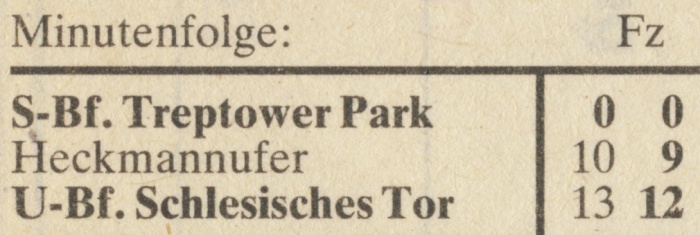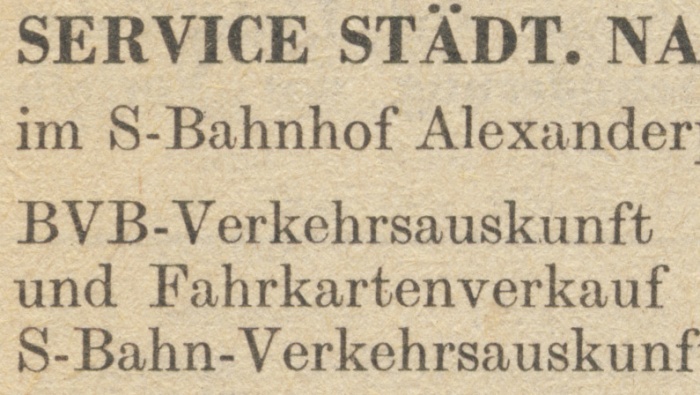
Schrift aus Fahrplanbuch gesucht
Es geht um 2 verschiedene Schriften aus alten Fahrplanbüchern.
Ist letztere eine Times New Roman?
Zur ersten habe ich gar keine Idee.
Zu der Zeit als deine Fahrpläne gesetzt wurden, gab es die Bodoni Twelve (ITC, 1994) wahrscheinlich noch nicht. Eher wird es so sein, dass der Fahrplan auf eine Lino- oder Intertype gesetzt worden ist. Eventuell auch Monotype. Einen Schriftwechsel zu einer anderen Schriftfamilie war damals für solche Werke viel zu aufwändig. Bei Linotype und Intertype standen immer zwei Schriften auf einer sogenannte Duplex-Matrize. Bei Monotype konnten bis zu drei Schnitte (normalerweise Normal, Kursiv und Fett oder Normal, Kapitälchen und Kursiv) einer Familie auf einem Matrizenrahmen kombiniert werden. In beiden Fällen kam normalerweise der fette Schnitt aus der gleiche Familie wie der normale Schnitt. Bei Linotype mussten die zwei Schnitte einer Matrize dicktengleich sein. Kombinationen wie fette Bodoni und normale Modern Extended wären eine kostspielige Sonderanfertigung gewesen. Bei Monotype konnte der Matrizenrahmen individuell bestückt werden, allerdings mussten alle Zeichen einer horizontale Reihe die gleiche Dickte aufweisen. Es gab aber noch weitere technische Gegebenheiten (uA die Justierung der Dickten), was dazu beigetragen hat, dass das ‘freie Einteilen der Matrize’ in der Regel auf den Einsatz von Sonderzeichen beschränkt blieb.
ja, mir ging es nicht darum (bzw. ich bin nicht in der lage), die nicht-digitalen originalschriftarten zu bestimmen, die verwendet wurden, um diese fahrpläne zu setzen. das, was ich genannt habe, waren die nächsten font-äquivalente, die mir in den sinn kamen.